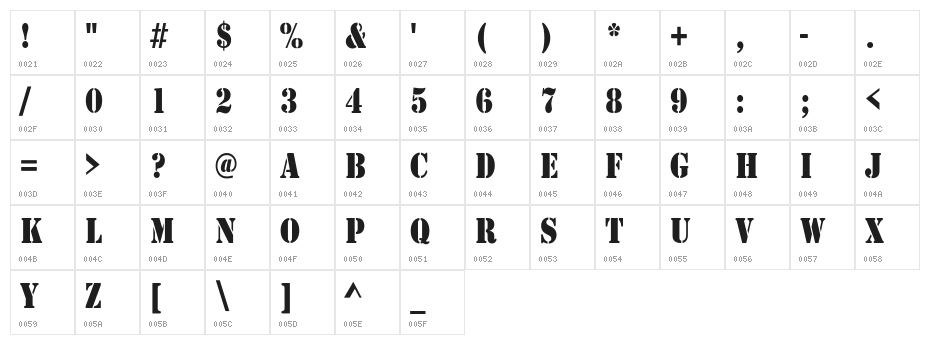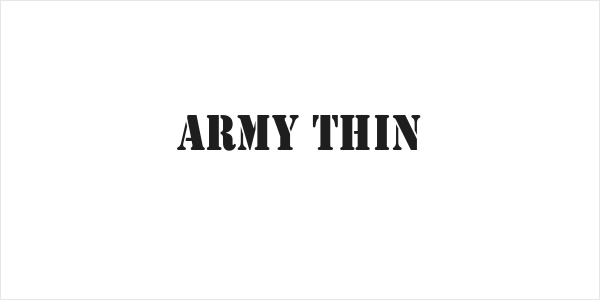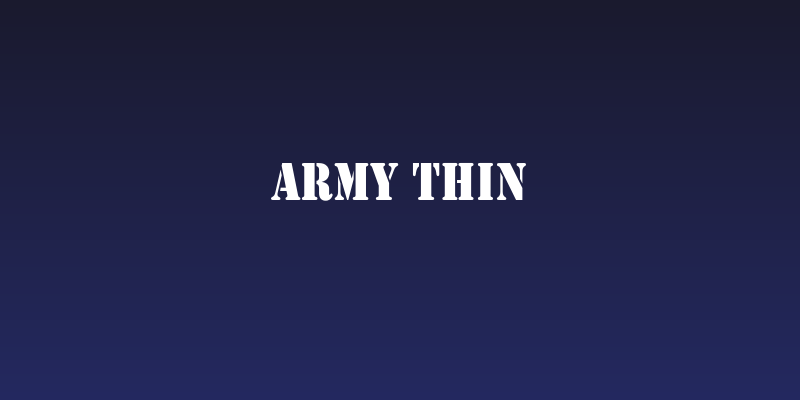
Army Thin Font
✎ Stencil
| Kategorien | Stencil |
| Gesamtstil | Modern, Military |
| Vorgeschlagene Projekte | Ideal for military-themed designs, posters, signage, and branding that requires a bold, authoritative presence. |